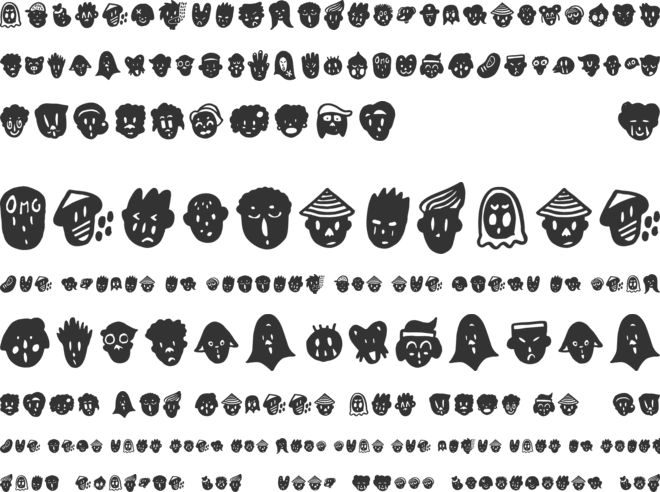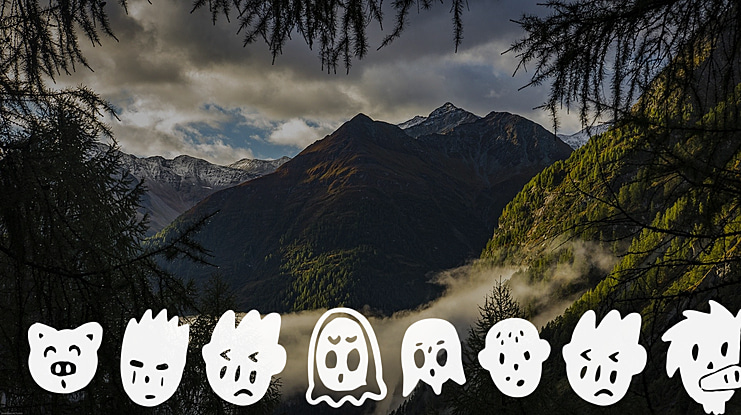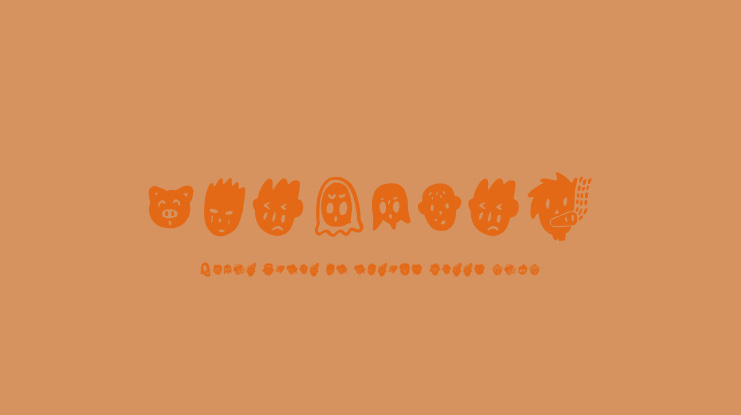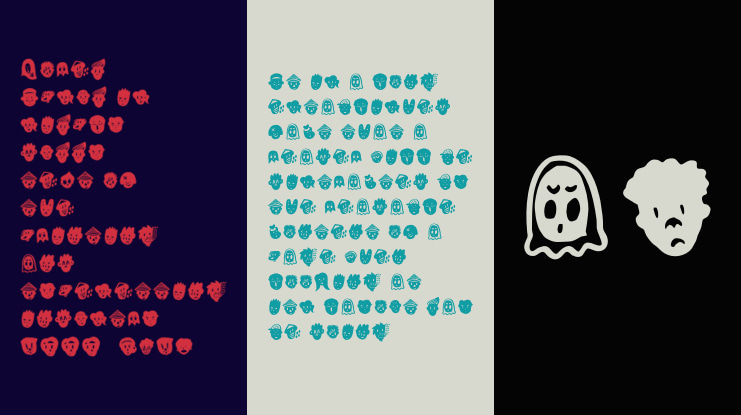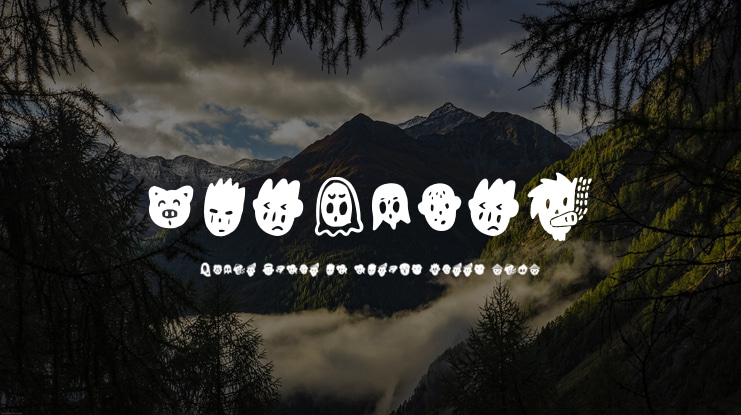
Binarung Font
Fontasi ini berisikan wajah-wajah manusia dan hewan atau bukan kedua-duanya. Mereka digambar dengan sekilas saja, langsung tanpa kesengajaan apa pun. Dari awal sampai akhir pembuatan font ini dilakukan di kamar asrama 9, Universitas Negeri Chonnam, Gwangju, Korea Selatan.
Binarung berarti 'bersama' atau 'ditemani' dalam bahasa Jawa.